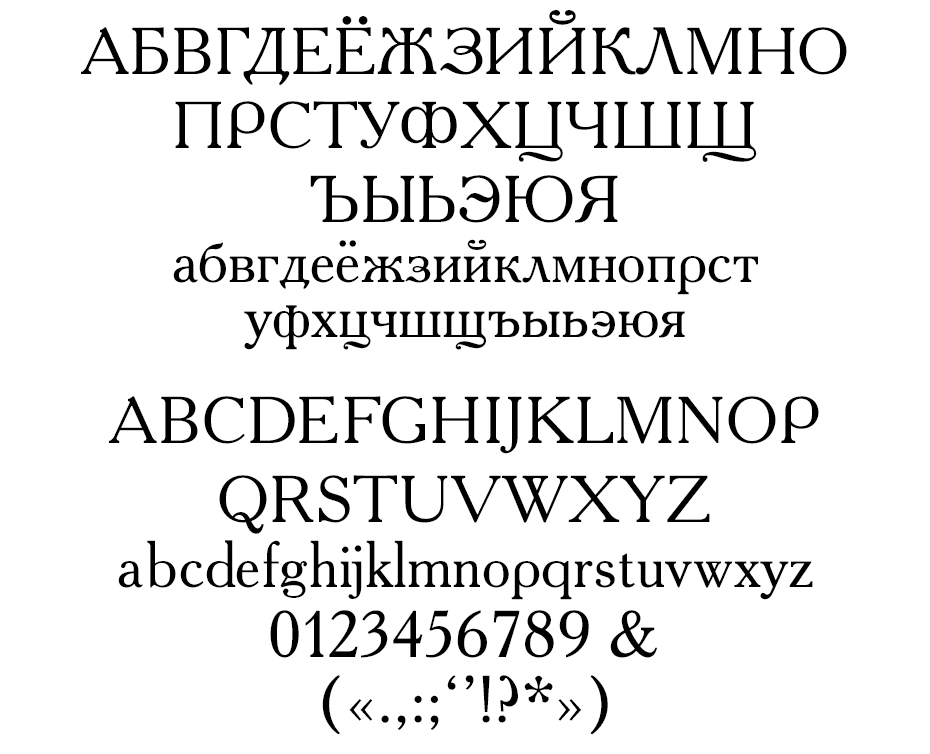
— Вы — художник. Как это помогает или мешает в коммерческих проектах?— Последнее время они позволяют мне быть художником. Это очень приятно. В частности, питерский проект «Тридцать Три Знака», который мы делали с Андреем Пуниным — он для меня был и коммерческим, и при этом безумно творческим.
Лабиринт кириллицы из проекта «33 Знака», в котором рассказывается об истории кириллицы. Помимо лабиринта, по Санкт-Петербургу было расставлено ещё 15 букв-скульптур от различных авторов. Фото: Центральный выставочный зал «Манеж»Лабиринт кириллицы из проекта «33 Знака», в котором рассказывается об истории кириллицы. Помимо лабиринта, по Санкт-Петербургу было расставлено ещё 15 букв-скульптур от различных авторов. Фото: Центральный выставочный зал «Манеж»Лабиринт кириллицы из проекта «33 Знака», в котором рассказывается об истории кириллицы. Помимо лабиринта, по Санкт-Петербургу было расставлено ещё 15 букв-скульптур от различных авторов.
Фото: страница Юрия Гордона в FacebookЛабиринт кириллицы из проекта «33 Знака», в котором рассказывается об истории кириллицы. Помимо лабиринта, по Санкт-Петербургу было расставлено ещё 15 букв-скульптур от различных авторов. Фото: страница Юрия Гордона в FacebookЭто был большой объект, стоявший около питерского Манежа. В нём было три маршрута, которые рассказывали об истории кириллицы: один был посвящён глаголице, другой — Петровской реформе, третий — письменности в послепетровское время и тому, о чём редко говорится, — истории русского письма.
Я думаю, что этот проект ещё возродится. Его просто разобрали и увезли. Скорее всего, если он будет ещё инсталлирован, то уже в Москве на ВДНХ.
— Как вы ищете настроение шрифта?
— Закрытый шрифт, как правило, более спокойный. Открытый — более гуманистический. Это самые общие вещи. Но есть и более тонкие.
Мой шрифт AntiQuasi получился весёлым, и страницы с ним становятся веселее. Я не то чтобы специально хотел этого добиться, но, пока этот шрифт делал, очень сильно смеялся. Видимо, он как-то подхватил эту весёлость в своей форме.
Шрифт AntiQuasi. Изображение: Юрий ГордонМы с Валерием хорошо знаем, как придать шрифту нужное настроение. Есть определённые формы, которые у читателей ассоциируются с определёнными эмоциями — мы используем это.
Но вообще, вопрос сложный. Это как спрашивать у поэта: «Как вы ищете свои рифмы?» или «Как вы используете метафоры?» Тоже метафорический ряд.
— Для чего компании может понадобиться уникальный фирменный шрифт?— В студии Letterhead сделано очень много шрифтов. И они были для очень разных заказчиков по очень разным поводам.
Если шрифт заказывает банк, скорее всего, его будут использовать в качестве ещё одного средства идентификации — не только для рекламы, но и в документообороте
в качестве уникального средства, которое эту институцию представляет.
Если шрифт заказывает публичная компания, вроде сетей супермаркетов или телеканала, они, как правило, будут использовать его в собственной репрезентации — в рекламных целях, аппликации, посвящённой деятельности этой компании.
Если шрифт заказывает кто-то вроде глянцевого журнала, это делается для изменения макета и для усиления выразительности типографических средств.
Это всё — совершенно разные цели, которые требуют разных средств выразительности и разного объёма набора знаков.
— Как вы обсуждаете задачу с клиентом?
— Для каждого случая свой собственный способ обсуждения. Если у компании есть дизайнерский отдел, мы общаемся с их арт-директором. Либо с арт-директорами агентств, которые работают на нашего заказчика. Бывает, что и напрямую приходится общаться с представителями компаний.
Когда люди к нам приходят, мы им задаём вопросы: какого объёма шрифт им нужен, какие языки он должен поддерживать, сколько начертаний, нужен ли вариатив, нужны ли какие-то специальные знаки, как он будет соотноситься с фирменным стилем.
На старте проекта эти вопросы должны быть решены с максимальной точностью.
Поэтому, как правило, этап с обсуждением довольно долгий. Мы всё подробно и аккуратно проговариваем с заказчиком, чтобы потом к этому уже не возвращаться. Это важно, так как у клиента уже есть в голове референсы — мы их должны увидеть.
Шрифт — это гора. Если ты что-то не так заложил в основание, потом всё время будет сходить лавина. Изменить шрифт в процессе создания страшно сложно. Поэтому мы стараемся на старте договориться обо всём.
Иногда бывают неформальные переговоры, но тогда результат может быть каким угодно. Например, Дима Барбанель — он был заказчиком множества моих шрифтов — может показать мне какую-то старую модель Volvo и сказать: «Смотри — это то, что мне нужно». А с кем-то мы разговариваем на уже более понятном для заказчика языке.
Если в процесс разработки включён поиск решения, то мы придумываем поисковое слово или фразу — несколько вариантов показываем заказчику.
Он выбирает, мы ещё раз редактируем на этой небольшой части шрифта, а потом уже строится вся гарнитура. Это каждый раз серьёзная подготовка. Более серьёзная, чем для любого другого вида дизайна.
Шрифт не терпит непроговорённости.
— Какой шрифт, сделанный для клиента, у вас любимый?
Преимущество ученых заключается в том, что они используют контролируемые эксперименты, измерения и расчеты для установления поддающихся проверке значений того, что происходит между графическими объектами, глазами и мозгом при малых размерах. Недостатком является то, что сами по себе научные открытия не дают достаточного руководства для разработки практических типов, приемлемых для большинства читателей, отчасти потому, что культурная история и эстетические стандарты иногда произвольны.Но наука может направлять дизайнеров, а дизайнеры могут создавать формы для изучения учеными, поэтому существует взаимность.
Критический размер печати